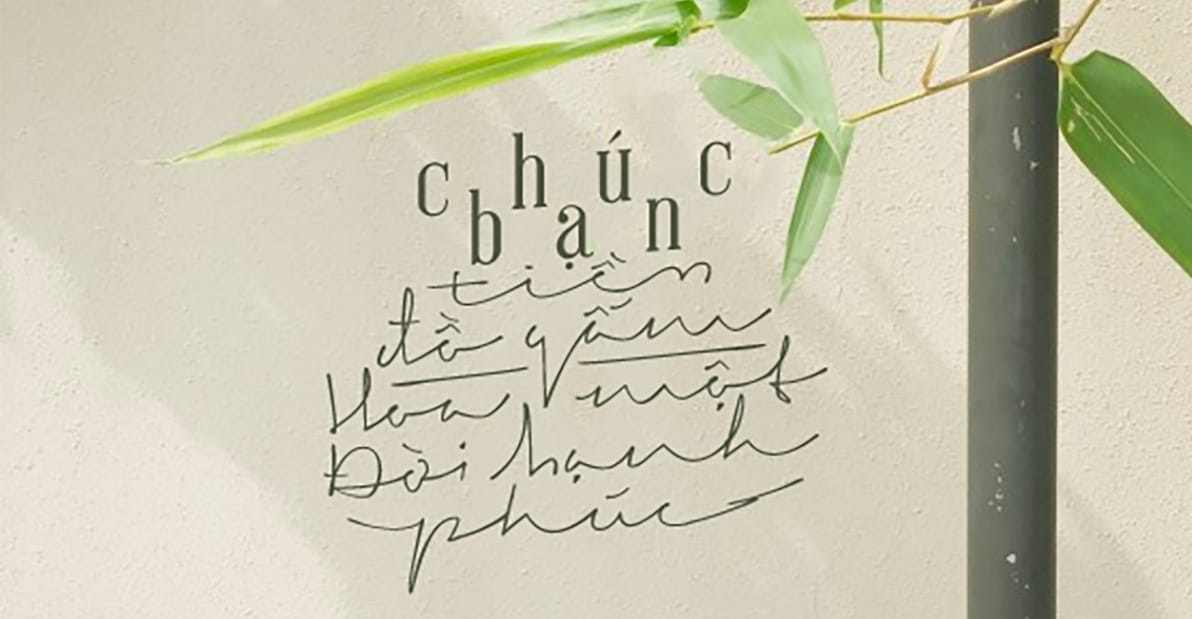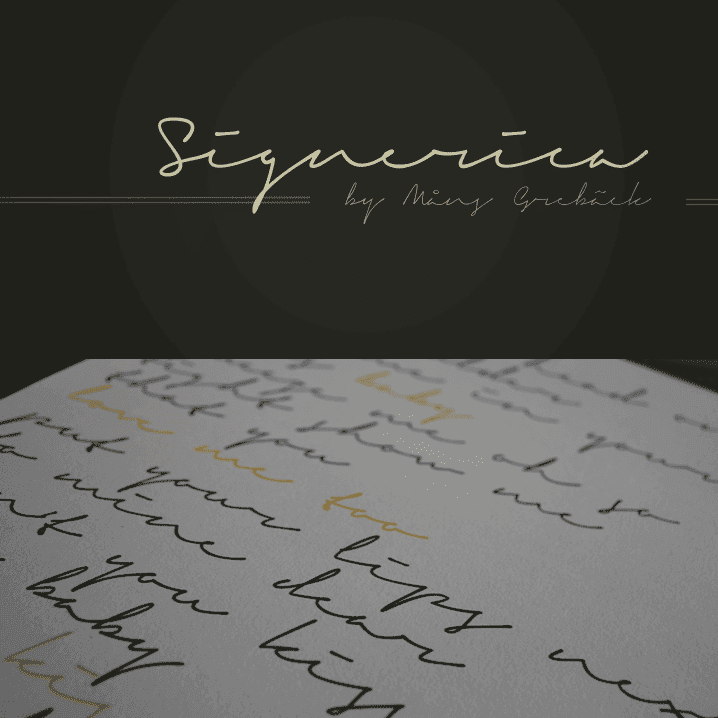
Font Signerica Việt hóa – Font viết tay
Font Signerica Việt hóa là một font chữ viết tay được thiết kế bởi Mans Greback, một nhà thiết kế font chữ nổi tiếng người Thụy Điển. Font chữ này đã được tải xuống hơn 2 triệu lần trên Dafont và là phông chữ phổ biến hàng đầu của nhà thiết kế. Dưới đây là link tải font SignericaVi Full đã được Việt hoá hoàn chỉnh.